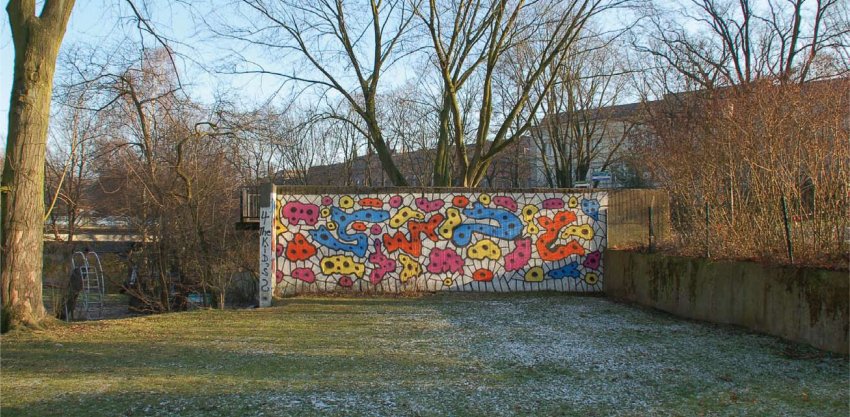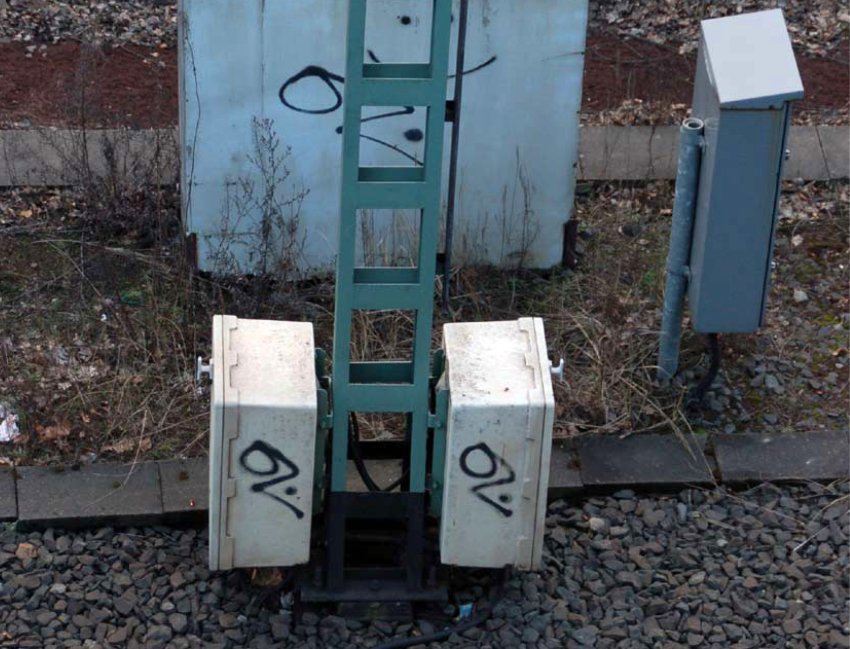
Ich bin ehrlich gespalten, was das Gesamtwerk angeht. Bei vielen Werken würde sich niemand wundern, wenn sie im MoMA hingen:
In anderen hingegen kann ich beim besten Willen nicht mehr sehen als Schmiererei:
Unterm Strich hat Hamburg gestern sicher verloren: solche Künstler gibt es kaum; solche Schmierfinken hingegen schon.
Ganz davon abgesehen, dass der Tag nicht OZ (wie Ostsee-Zeitung) heißt, sondern eigentlich Oli bedeutet (drum der Punkt)
Ich war übrigens mal auf den Typ alles andere als gut zu sprechen,  hatte er doch das Plexiglas-Oberlicht meiner damaligen Werkstatt zuerst mit Felgensilber zugemalt, und dann seinen Tag (den großen eckigen) drauf gestaltet. Das tat dem Plexiglas gar nicht gut, es wurde von der Verdünnung rissig und drohte in meine Werkstatt zu krümeln, und kostete mich für die dann nötige Sonderanfertigung der Neuverglasung 570 Mark. Hääte ich nicht die Montage mit Hilfe meines Kollegen selbst hin bekommen, wär ich wohl weit über 1000 Mark los geworden. In so fern hält sich meinme Trauer in grenzen.
Tja, so ist das mit den Ligaturen: manchmal verwirren sie eher statt zu helfen. :baeh:
Sorry wegen deines Oberlichts; ich kann deinen Ärger gut verstehen. Hast du die verunstaltezierte, aber auf jeden Fall nicht mehr oberlichttaugliche, Scheibe behalten?
nein, die zerbrach schon beim Abbau und ging dann in den Müll.
Nach Ersetzen des Oberlichtes wurde die "Zerstörung des Kunstwerkes" dann mit den Tags, wie auf den Bahn-Schaltkästen vergolten, der dann gleich mehrfach auf meinen Rollläden  zu finden war.
Aber die sahen neu lackiert ohnehin hinterher besser aus, als die doch schon etwas verwitterte Originaloberfläche.
Ich hatte aber echt überlegt, ob ich nicht irgendwie einen Verdünnung-Sensor installieren könnte, der dann wiederum eine Spritzpistole hinter den Spalten der Rollläden aktiviert, die dann zurück sprayt.
Jahre später hab ich das dann im Fernsehen gesehen, War so ein Sketch, in dem "die neuste Entwicklung gegen Sprayer" gezeigt wurde. Das war allerdings eine Wand, die dann den Sprayer gelb lackierte. Ich glaube das war von Mr Bean, bin mir aber nicht sicher.